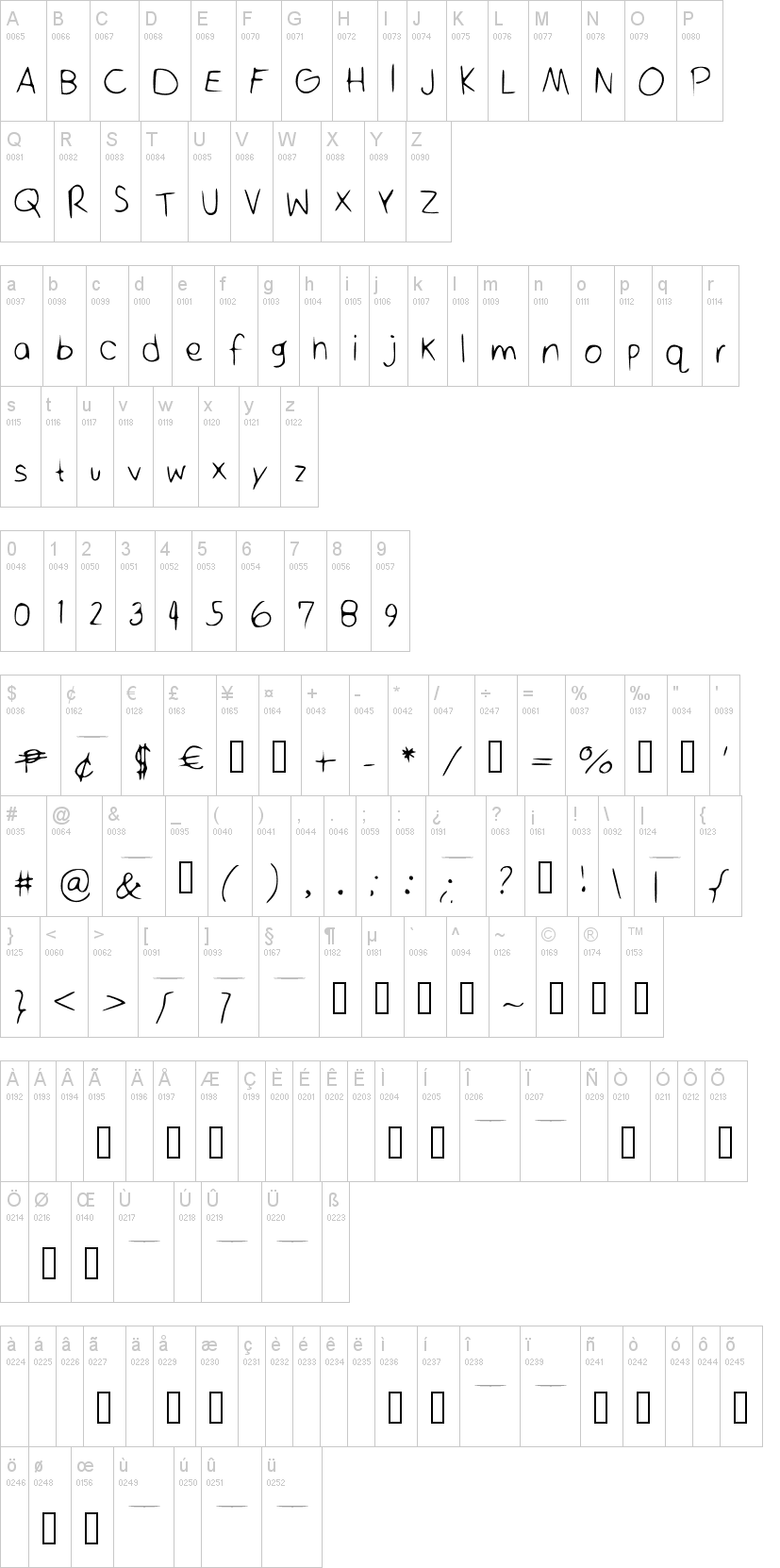
Oh Hello
? Oh Hello 是一款简洁又时尚的字体,它由美国设计师Jeremy Vessey设计,以其古典复古风格和优雅的曲线而闻名。Oh Hello字体可以用于各种不同的设计项目,包括印刷、网页设计、平面设计、标志设计等等。它的特点是清晰的字母形状和宽松的字体间距,使文本显得简洁而优雅。
Oh Hello是一款非常不错的手写艺术字体,具有很好的视觉感,适合于文化类的宣传设计、商业类品牌的广告和产品包装设计以及个性化文字排版等较多场景。
Oh Hello字符映射图